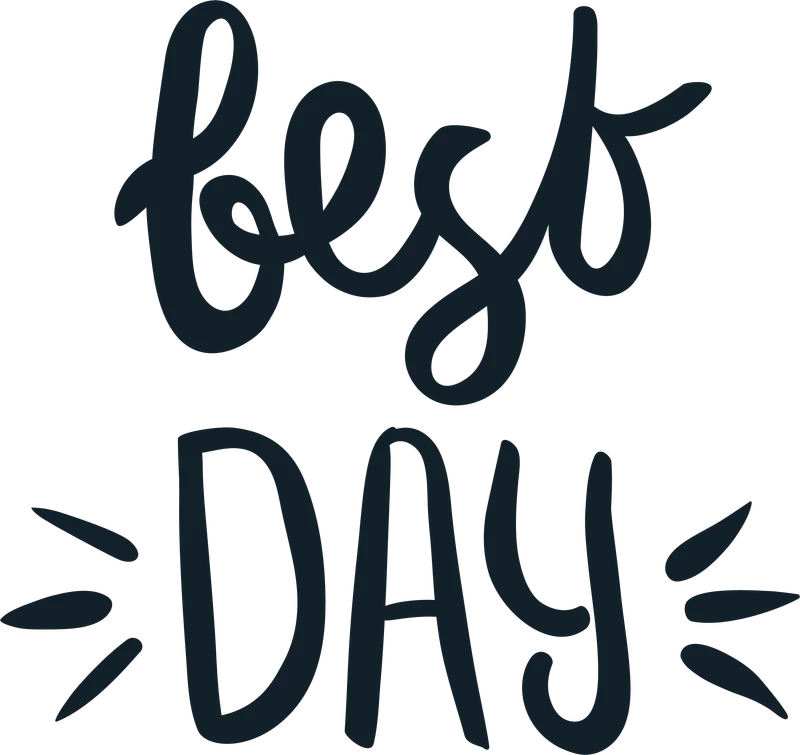
Lời chúc "Best Day" ý nghĩa, font chữ thư pháp độc đáo
Lời chúc "Best Day" ý nghĩa, font chữ thư pháp độc đáo — In hình chữ "Best Day" với font thư pháp độc đáo, mang thông điệp tích cực. Phù hợp in lên áo, túi tote, cốc, sticker tạo phong cách riêng.
Trong hình có: lời chúc
Phong cách: line-art · Cảm giác: vui
Tông màu chủ đạo: xám